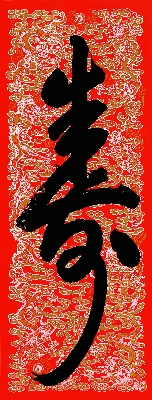
乾隆
乾隆简介
乾隆皇帝,即清高宗(1711一1799),爱新觉罗·弘历,世宗四子。清代皇帝,1735一1795年在位。继位后,先后讨平西北、西南,抗击廓尔喀入侵,拒绝英使马戛尔尼的无理要求,鼓励垦荒,颁布禁书令,迭兴文字狱,开四库全书馆,编纂《续三通》、《皇朝三通》等。晚年,自号十全老人,陶醉于文治武功,听任和砷专权,日益腐败。乾隆一生酷爱书法,历经数年,刻意搜求历代书法名品,御览、御批、钦定多部传世藏帖,集我国历代书法艺术之大成。大学士梁诗正等赞曰:“皇上性契义爻,学贯仓史,每于万机之暇,深探八法之微。宝翰所垂,云章霞采,凤翥龙腾。综百氏而集其成,追二王而得其粹。又复品鉴精严,研究周悉,于诸家工拙真赝,如明镜之照,纤毫莫遁其形。仰识圣天子好古勤求,嘉惠来学,甄陶万世之心,有加无已。”   >>更多详细
清 乾隆 御笔大士像并心经图纸本25x56
[1083]清 乾隆 御笔大士像并心经图纸本25x56
泥金书四得续论-清-高宗弘历
[32]泥金书四得续论-清-高宗弘历
清 乾隆 乾隆帝元宵行乐图轴60x41
[5207]清 乾隆 乾隆帝元宵行乐图轴60x41
清 乾隆 御笔玉泉山竹炉山房楷书册和田玉165x 104cm切斯特藏
[95864]清 乾隆 御笔玉泉山竹炉山房楷书册和田玉165x 104cm切斯特藏
清 弘历 楷书临玉枕兰亭序卷38x419cm故宫
[95818]清 弘历 楷书临玉枕兰亭序卷38x419cm故宫
清 高宗弘历 御笔诗经全图书画合璧图册43.5x43cm台北
[95807]清 高宗弘历 御笔诗经全图书画合璧图册43.5x43cm台北
清 乾隆 御制晚年论文册玉书129x 83cm切斯特藏
[95867]清 乾隆 御制晚年论文册玉书129x 83cm切斯特藏
清 乾隆 御笔大士像并心经图纸本25x56
[1971]清 乾隆 御笔大士像并心经图纸本25x56
清  乾隆石鼓文序  民国拓本
[98979]清 乾隆石鼓文序 民国拓本
清 乾隆 寿纸本56X150
[1082]清 乾隆 寿纸本56X150